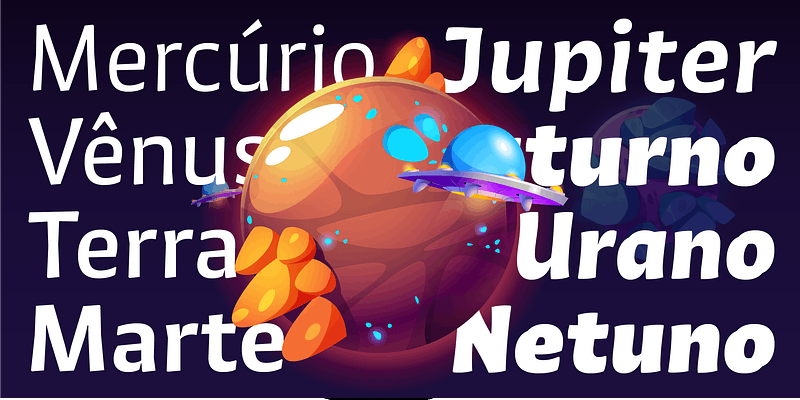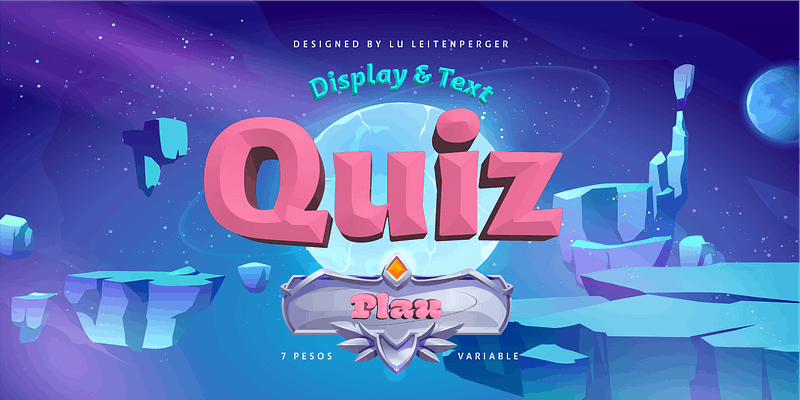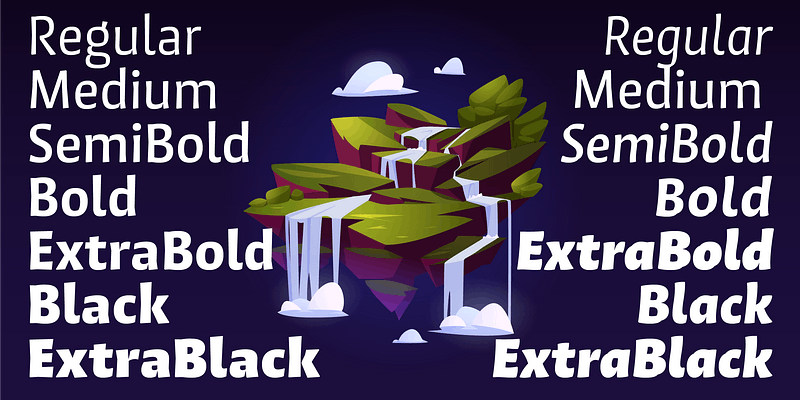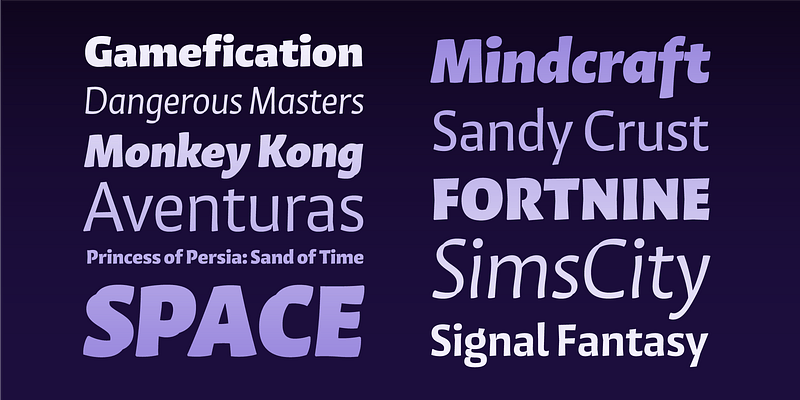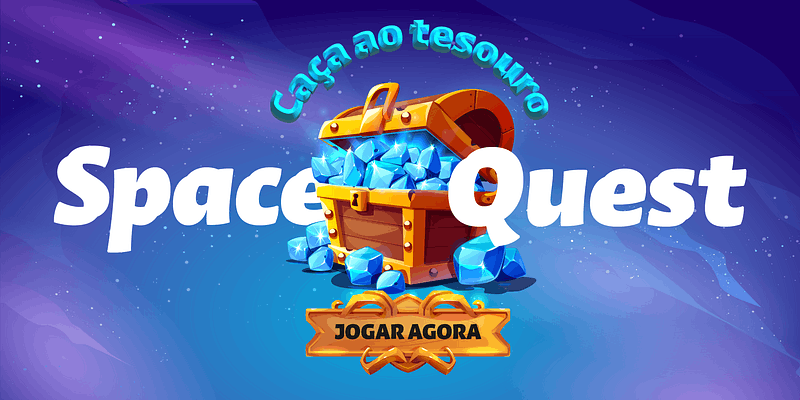
Lu Leitenperger가 디자인한 Romans는 뭉툭한 산세리프체를 전문적으로 연출한 서체로, 평범함과는 거리가 멉니다. 이탤릭체는 역동성이 급진적으로 변화하고 그 과정에서 매우 친근해지는 그 자체의 장입니다. 퀴즈에는 다양한 글꼴 기능이 있으며 각각 14가지 스타일이 포함된 두 가지 광학 크기로 제공됩니다.